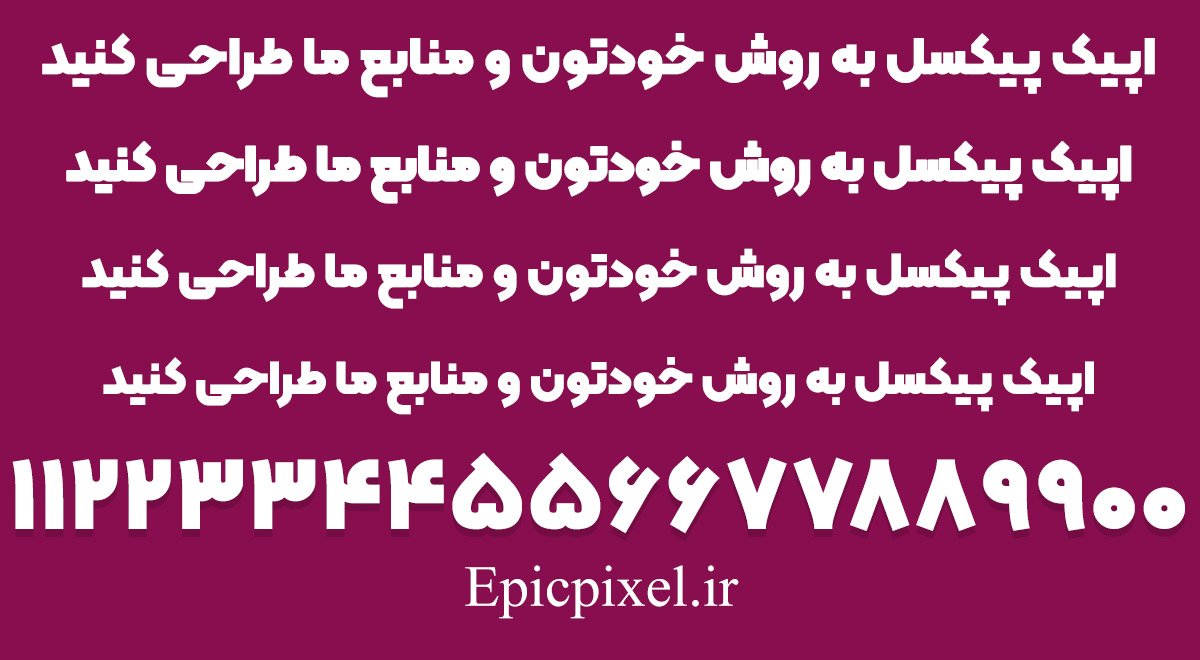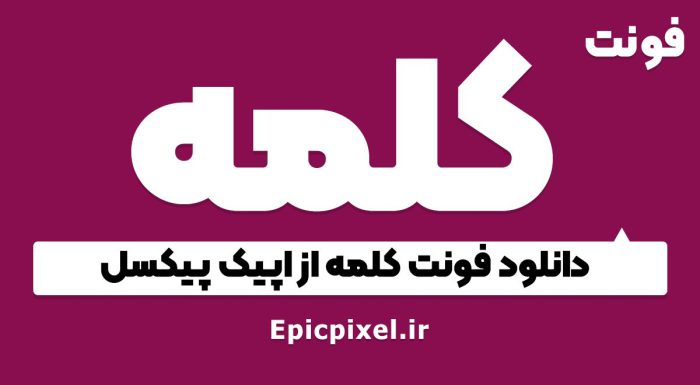
فونت کلمه، با ساختار هندسی و منظم خود، ظاهری شیک و مدرن به نوشته های شما می بخشد و برای استفاده در طراحی های گوناگون، به ویژه تبلیغات و فضاهای دیجیتال، گزینه ای ایده آل است. این فونت، با وجود پویایی و انرژی اش، خوانایی بالایی دارد و در اندازه های مختلف، چه در عناوین بزرگ و چه در متن های طولانی، به خوبی دیده می شود.
یکی از ویژگی های برجسته کلمه، پشتیبانی از زبان های فارسی، عربی و انگلیسی است که آن را به انتخابی مناسب برای پروژه های چندزبانه تبدیل می کند. همچنین، این فونت از زبان های اردو و کردی نیز پشتیبانی می کند که دامنه کاربرد آن را گسترده تر می سازد.
فونت کلمه، با وجود ظاهر مدرن و جذابش، ممکن است برای متن های بسیار رسمی یا سنتی، انتخاب مناسبی نباشد. همچنین، به دلیل طراحی خاص خود، در برخی موارد خاص، ممکن است نیاز به تنظیمات جزئی در فاصله گذاری بین حروف داشته باشد. با این وجود، قدرت و خودنمایی این فونت در برجسته کردن ویژگی ها و نکات مهم متن، آن را به گزینه ای قدرتمند برای طراحانی تبدیل کرده که به دنبال ایجاد تمایز و جذابیت در آثار خود هستند. اگر به دنبال فونتی هستید که هم زیبا و مدرن باشد و هم خوانایی بالایی داشته باشد، فونت کلمه می تواند انتخاب بسیار خوبی برای شما باشد.